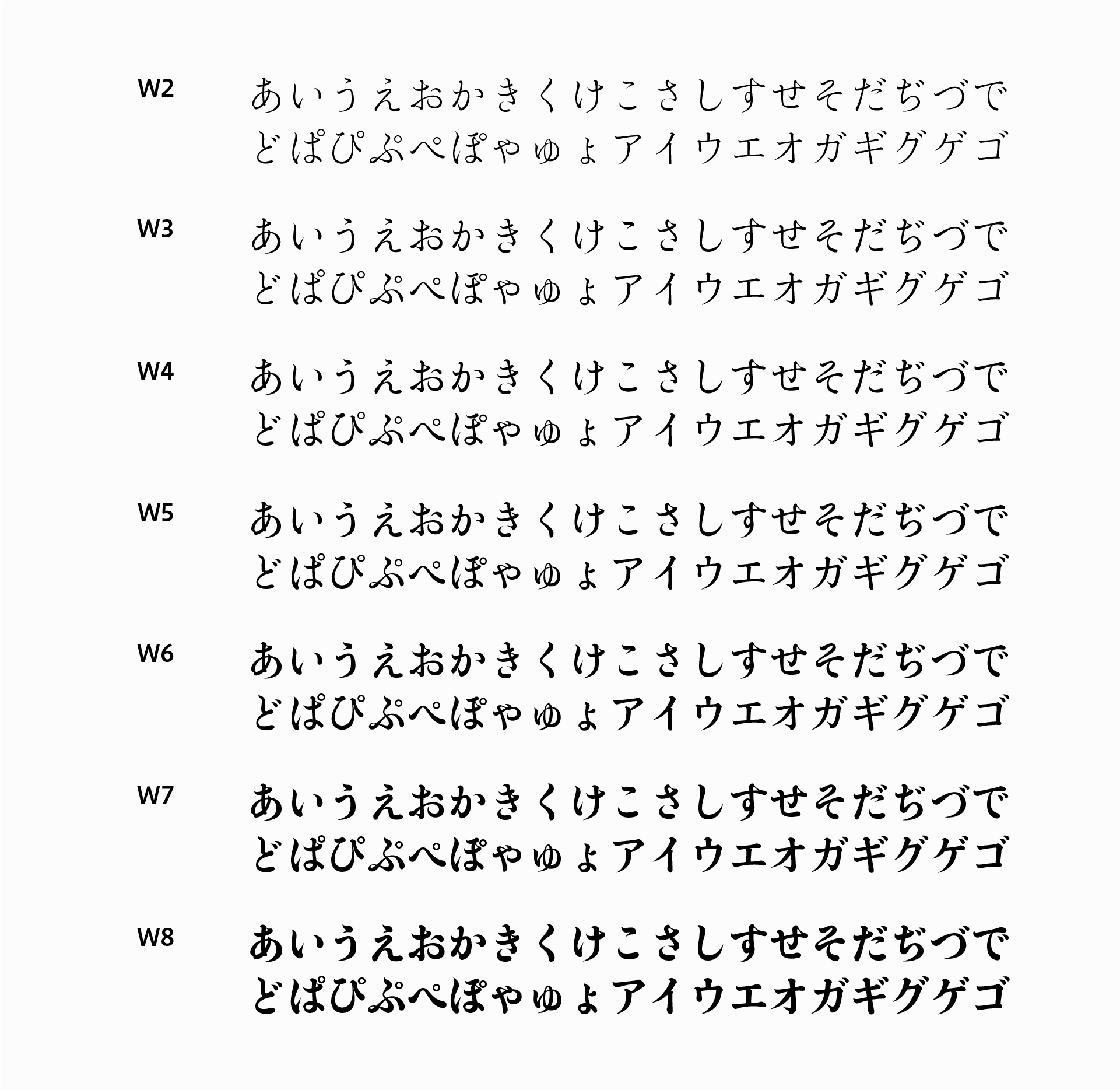
游築36ポ仮名は、明治から大正にかけて東京築地活版製造所が見出し用として提供して以来、情感豊かな書体として評価されてきた「36ポイント明朝体」がもつ伝統的な骨格を、字游工房が新しい感覚でリファインした仮名書体です。大きさ、太さ、寄り引き、姿勢、空きの関係をすべて見つめなおしました。そしてオリジナルは金属活字であるため、W5あたりの太さ一種類のみでしたが、ヒラギノ明朝の漢字と組み合わせて使うことができるよう、W2~W8まで7ウエイトすべてを用意、幅広い用途で使えます。すなわち、活字には存在しなかったW6~W8という、より強い見出しに使える太仮名や、より繊細なW2~W4という本文用の細仮名も使えるようになりました。それはまさしくデジタル飜刻ならではのメリットです。